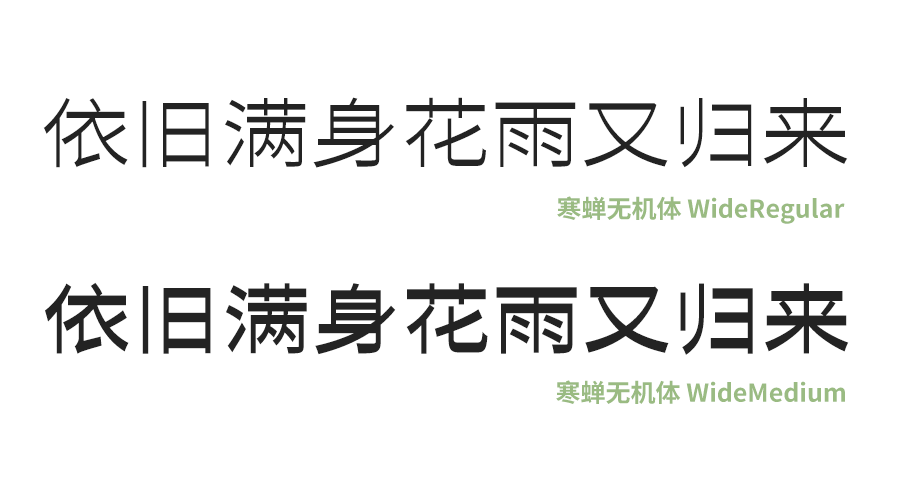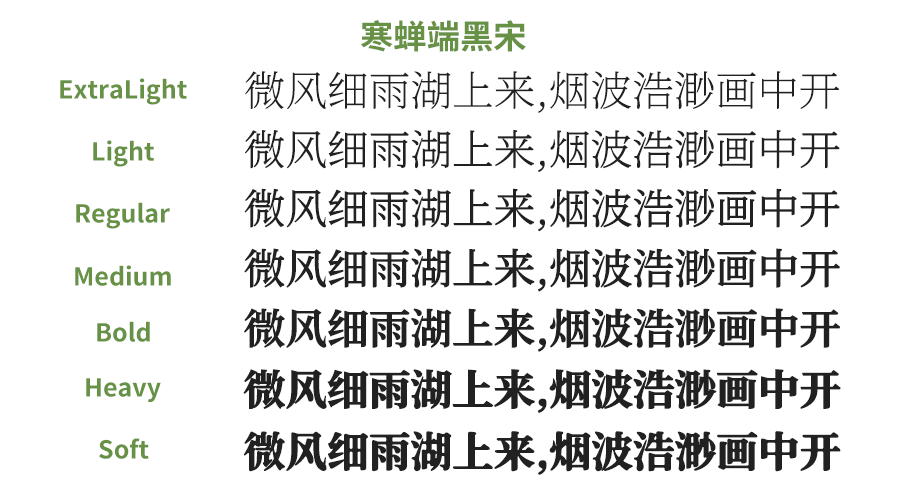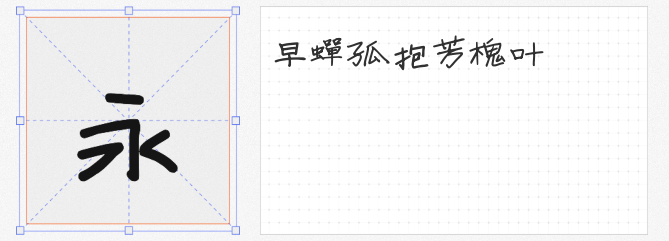
「寒蝉」系列字体以「传统解构」与「现代重构」为核心理念,打造出兼具文化厚度与实用价值的免费商用字库。四款字体各具锋芒,为设计师提供从古典雅致到先锋实验的全场景解决方案。
1.寒蝉龙藏楷书
承袭开源字体龙藏体的筋骨,以唐代楷书为蓝本重构数字字形。笔画温润如玉石,结构严谨似钟鼎,在保留传统书法「永字八法」精髓的同时,优化字腔比例使其更适配屏幕显示。字体一共有四款字重,字重顺滑的加黑,能多方面的适用于设计中。适用于古籍研究、文化品牌等需要古典气韵的场景,让数字文本焕发宣纸墨香。
2.寒蝉端黑宋
开创性地融合黑体力量感与宋体书卷气,横向笔画加粗处理形成视觉重心,竖笔末端保留优雅饰角。这种「刚柔并济」的设计使其既能承载科技产品的现代感,又适配传统文化项目的庄重需求。作为黑宋过渡字体,完美解决「黑体过刚易折,宋体过柔难显」的行业痛点。
3.寒蝉无机体 Wide
基于思源黑体进行「逆反差」美学实验,通过压缩竖笔、延展横画创造视觉张力。宽体设计强化几何切割感,负空间处理暗合水墨飞白意境,在极简主义与装饰艺术间找到精妙平衡。适用于潮牌海报、赛博朋克风格界面等先锋设计领域。
4.寒蝉手拙体
以「不完美即完美」为创作哲学,刻意保留手写体的颤抖笔迹与结构偏移。每个字符都带有温度感,仿佛可见书写者运笔时的呼吸节奏。虽不适用于正文排版,却是LOGO设计、艺术展览标题的绝妙选择——当刻意规整的字体泛滥时,这份笨拙的真诚反而成为稀缺价值。
四款字体构成完整的设计语言体系,给作品注入人性温度。更可贵的是全系列支持免费商用,让优质字体资源真正成为设计民主的推手。